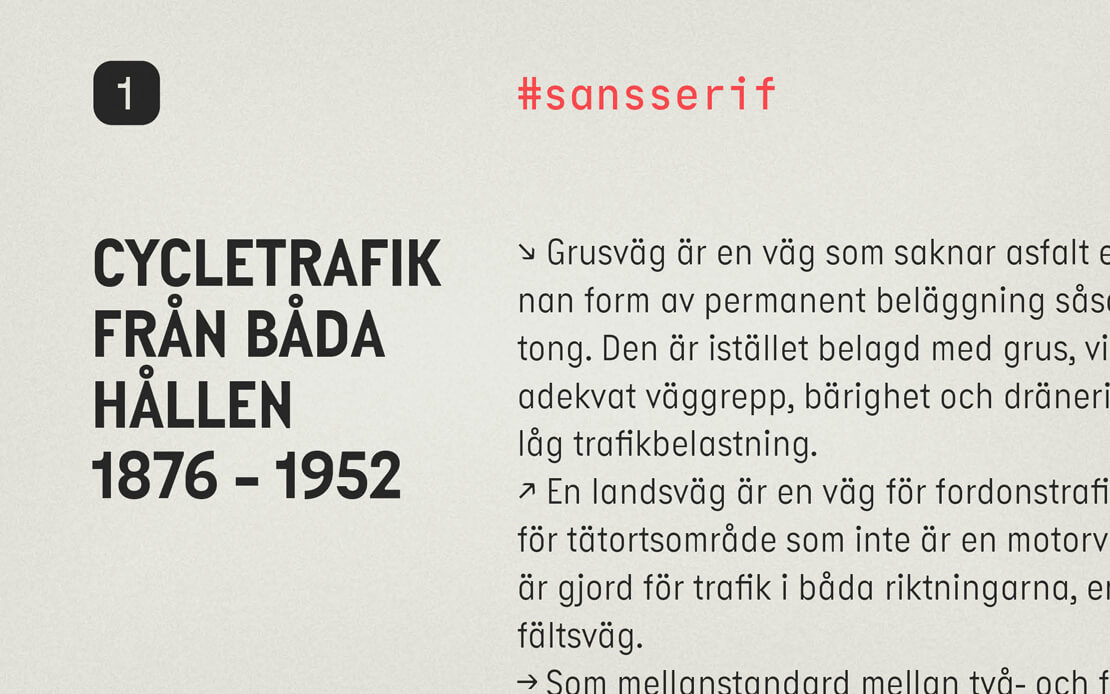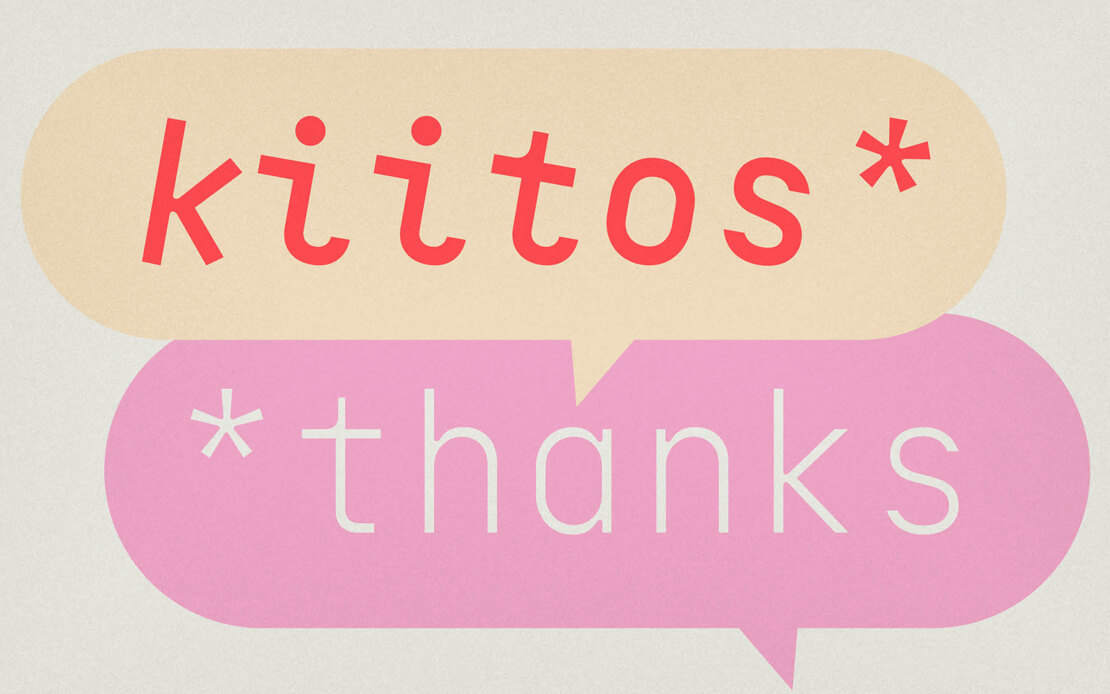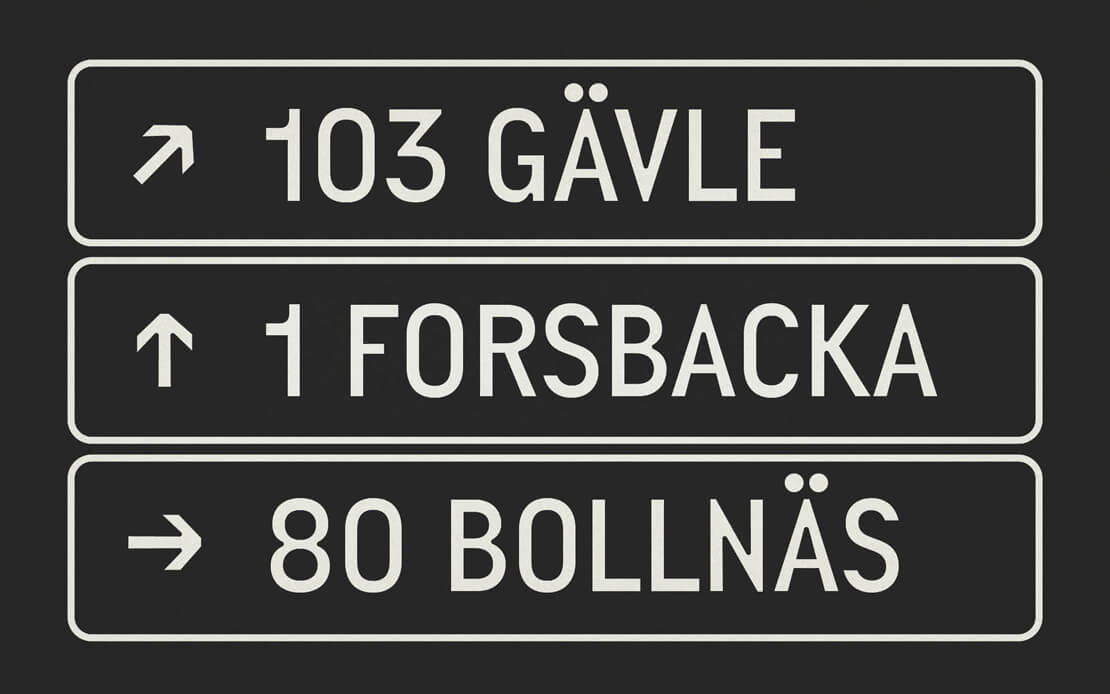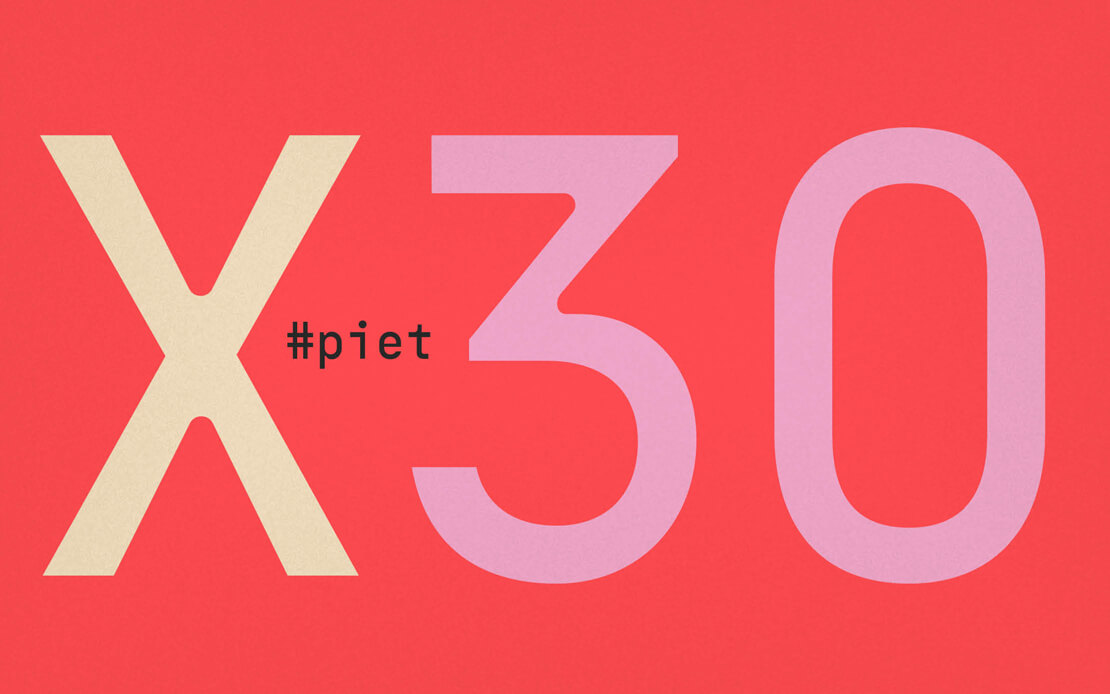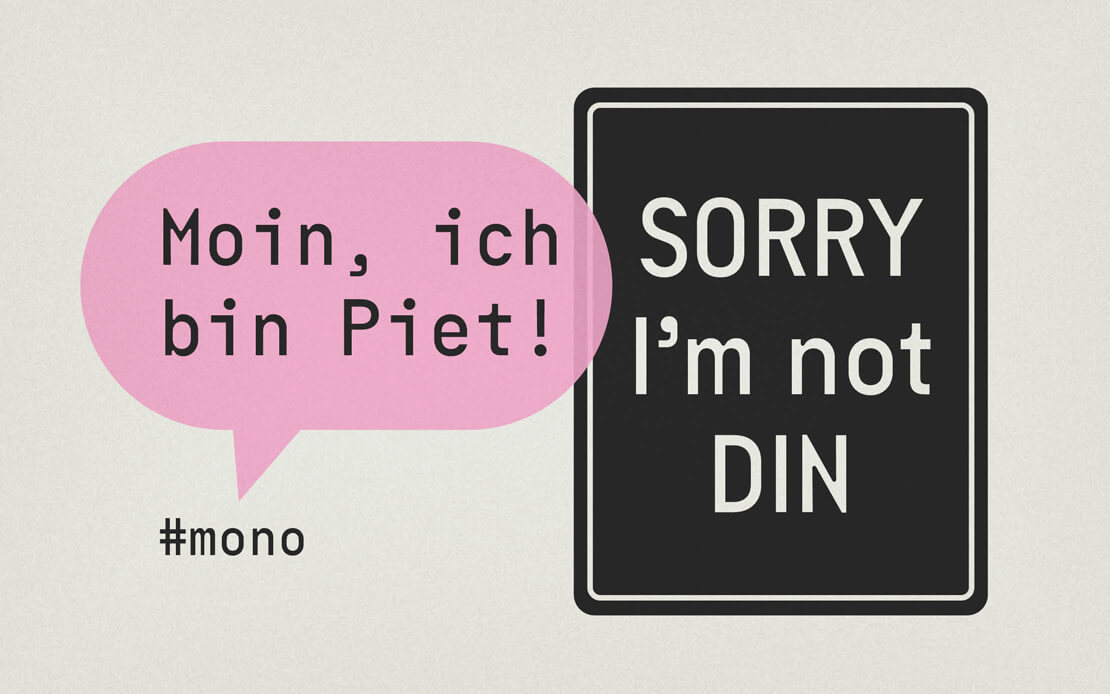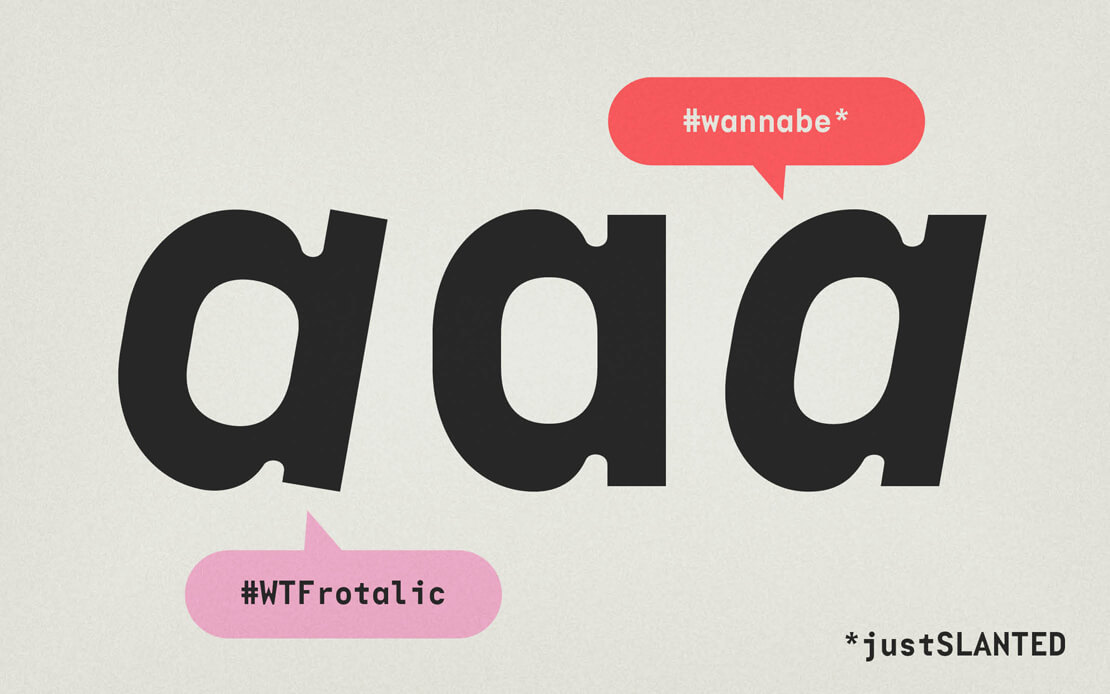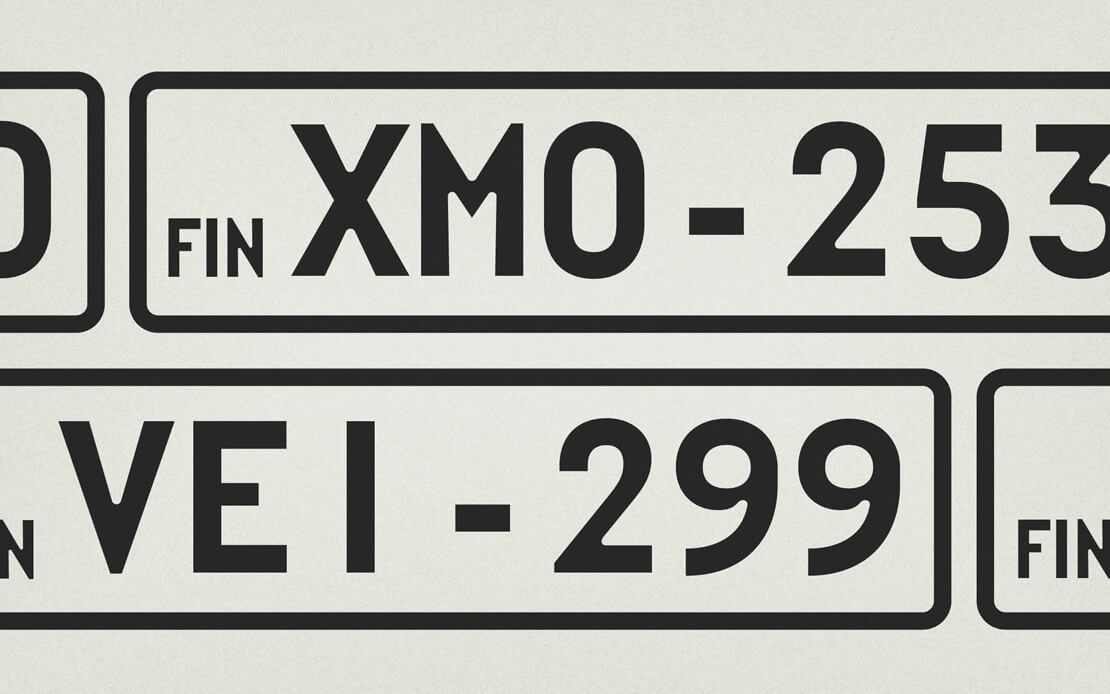
»Piet« bei TypeMates erschienen
Die neue Schriftart »Piet«, die bei TypeMates erschienen ist, zieht ihre Inspiration aus finnischen Nummernschildern. Sie zielt darauf ab, eine Synthese aus Strenge und Lebendigkeit zu schaffen.
Piet präsentiert sich als strenge und spielerische Schrift zugleich. Sie besticht durch ungewöhnliche Ziffern und tiefe, abgerundete Ink-Traps. Was auf den ersten Blick bürokratisch erscheint, offenbart bei einer zweiten, genaueren Ansicht eine Verbindung des Starren mit dem Lebendigen und der Kursiven mit einer gewissen Dynamik.
Die von Nils Thomsen gestaltete Piet umfasst zwei Schriftarten: die MONO und die Sans. Sofern die MONO für den geplanten Einsatz zu streng erscheinen sollte, bietet die Sans die Möglichkeit, eine Stufe lässiger zu werden.
Die Sans wurde auf Basis der MONO entwickelt, wobei Proportionen und Kerning Überarbeitungen erfuhren. Außerdem wurde die Schrift mit weicheren Formen versehen, um die Lesbarkeit zu verbessern.
Piet Sans und MONO bieten jeweils vier Schnitte, ergänzt durch ihre bisweilen unkonventionellen Kursiven. Zudem ist das Schriftdoppel mit verschiedenen OpenType-Features ausgestattet. Mit Funktionen wie tiefgestellten Ziffern, Brüchen, Tabellen- und proportionalen Ziffern, stilistischen Alternativen etc. stehen viele typografische Möglichkeiten bereit.